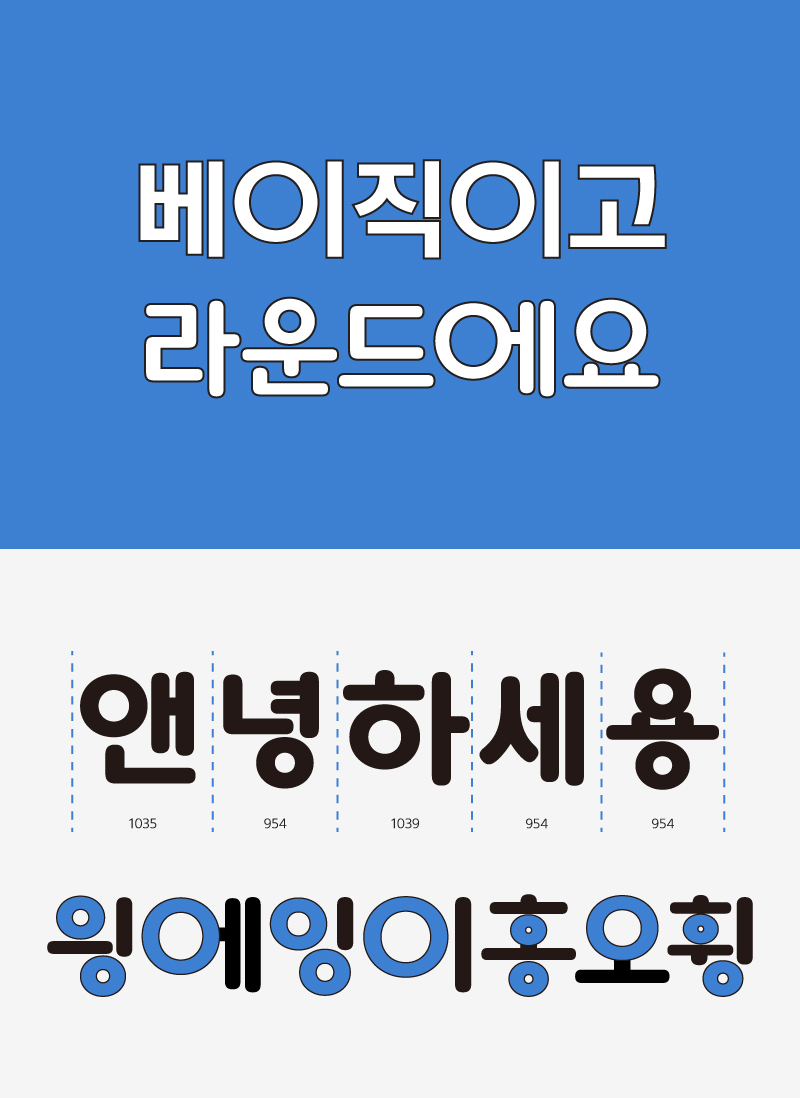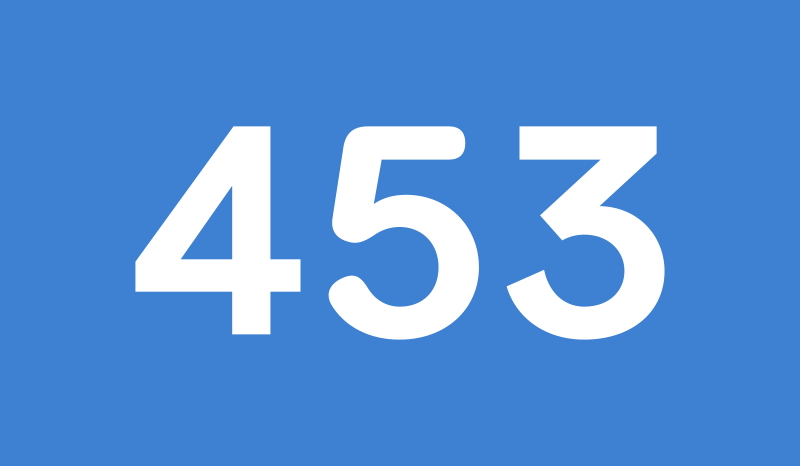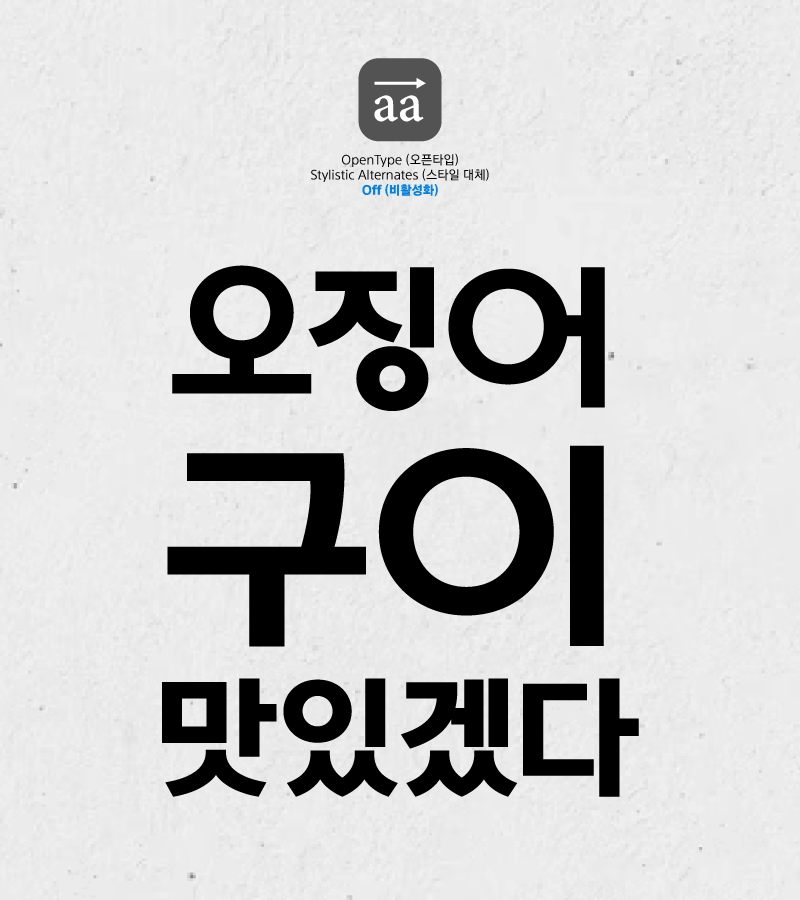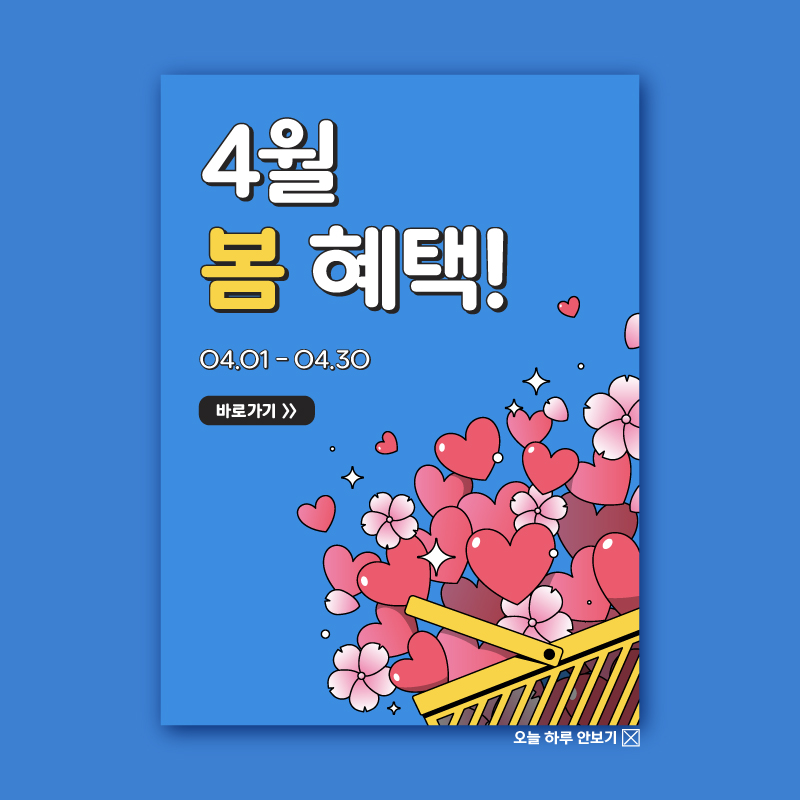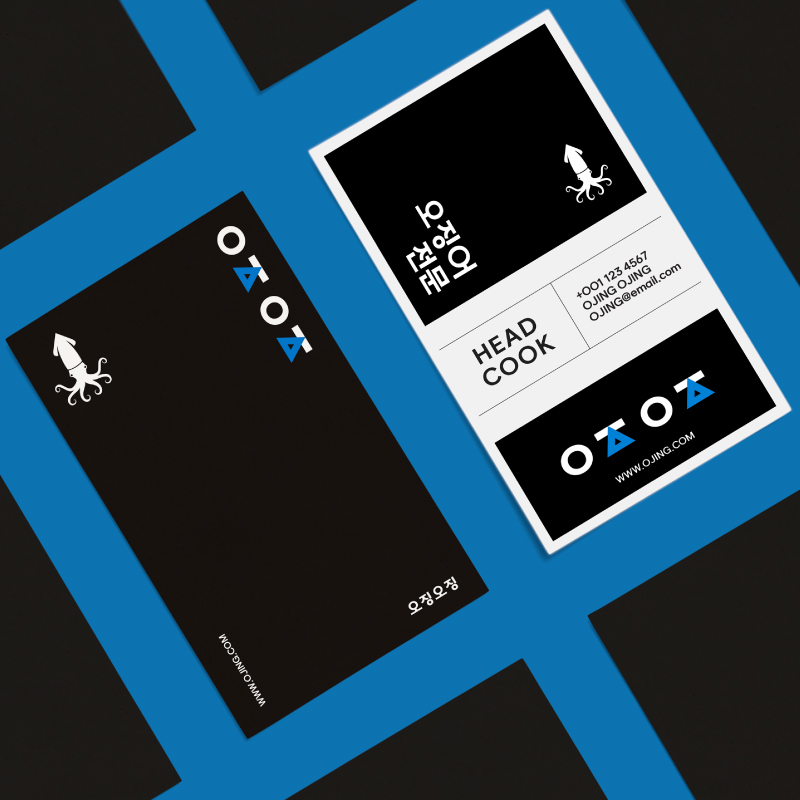
Rix오징어
2 종 - Basic, Round정원 형태의 자소 ‘ㅇ’을 중심으로 자폭과 공간이 변화하는 유쾌한 서체입니다.
깔끔한 이미지의 Basic과 귀여운 Round 두 가지 패밀리로 다양하게 활용할 수 있습니다.
일부 자음에 오픈타입 효과를 사용해 ○, △, □ 형태의 그래픽을 적용할 수 있습니다.